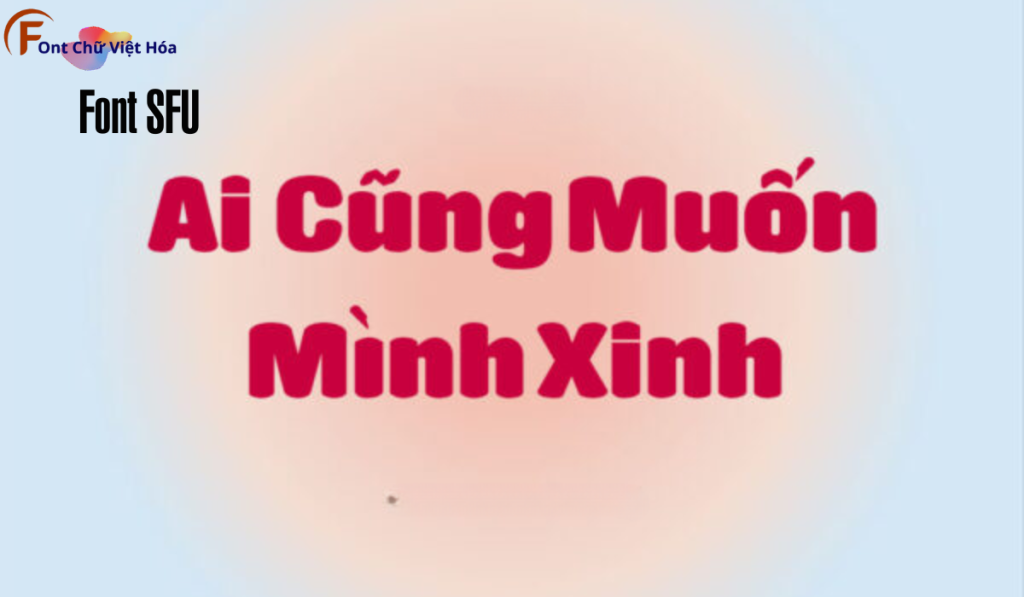
SFU Rhy Font Việt Hóa
Tác giả: SFU
Bộ Font: SFU
Phân loại: cá tính
Kiểu chữ: không chân
Font SFU Rhy Việt Hóa là một font chữ độc đáo, mang phong cách sans-serif hiện đại với các đường nét thanh thoát và tinh tế, thuộc bộ font SFU. Thiết kế của SFU Rhy tập trung vào sự rõ ràng và dễ đọc, đặc biệt phù hợp cho các thiết kế đòi hỏi tính thẩm mỹ cao như poster, logo, và tiêu đề. Với tỷ lệ chữ cân đối và các đường nét sắc sảo, font này tạo ra ấn tượng thị giác mạnh mẽ và giúp tối ưu hóa không gian trong thiết kế. Font này cũng đã được Việt hóa, mang đến sự linh hoạt và tiện dụng cho các dự án thiết kế bằng tiếng Việt.